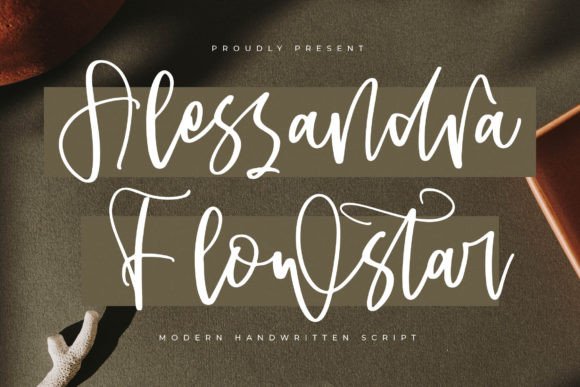
Alessandra Flowstar
Alessandra Flowstarのような高品質の素材をお探しの場合、このプレミアムパッケージはクリエイティブなプロジェクトに素晴らしい選択です。
精密に作られたAlessandra Flowstarは、クリーンなベクター、滑らかなタイポグラフィ、そして安心のための商用ライセンスを提供します。
POD(オンデマンド印刷)製品、結婚式の招待状、またはソーシャルメディアのグラフィックを作成している場合でも、Alessandra Flowstarは理想的です。